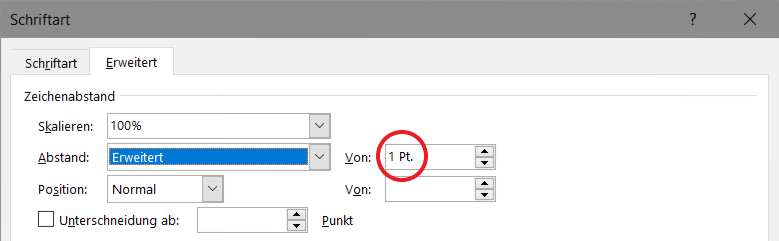
Schrift-Kombi für Projektarbeit im Bereich der Geschichtswissenschaften
Basiert nicht die ganze Diskussion darauf, dass es von Seiten der Hochschule die Vorgabe „12 pt“ gibt? Eben ohne zu Berücksichtigen, dass diese Angabe eigentlich völlig sinnlos ist. Und dann ist es eben doch irgendwie sinnvoll für diese Situation einfach mal diverse Schriften in 12 pt bezüglich der daraus resultierenden Seitenanzahl zu vergleichen. Der eine freut sich, dass er die geforderten zehn Seiten voll bekommt, der andere, dass er es schafft, so seinen Text auf zehn Seiten zusammenzustauchen.
Lesbarkeit, Mittellängen, Grauwert, ... alles unwichtig.
Wenn es so ist, verstehe ich es. Dann geht es nicht um Mittellängenvergleich, sondern um beliebige Verformungen zwecks Verschleierung des Umfangs. Nur wie sollte jemand den Schriftgrad auf einem Stück Papier oder in einem PDF überprüfen? Die Erfüllung dieser »sinnlosen« Vorgabe ist mit unterschiedlichen Schriften nicht nachprüfbar. Die Vereinheitlichung der abzugebenden Dokumente ist durchaus sinnvoll, um den Umfang vergleichen zu können. Früher war das die Normseite von 1800 Zeichen pro A4-Seite (30 Zeilen à 60 Anschläge).
Meine Herangehensweise wäre: Die Hochschule verlangt 12 Punkt und schreibt Arial oder Times New Roman vor. Das ist zwar einerseits unsinnig von Seiten der Hochschule, öffnet mir aber Freiräume. Nun möchte ich weder Arial noch Times New Roman verwenden, sondern ich suche mir eine  Alternative, die »irgendwie« nach Times aussieht. Und da ich nicht Martin Schröder bin, gibt es für mich hier auch nicht »die am besten geeignete Schrift«, sondern ich kann mir völlig schmerzfrei und ohne schlechtes typografisches Gewissen eine Schrift aussuchen, die mir bei gleicher optischer Größe (meinetwegen angelehnt an eine Times New Roman in 12 Punkt, damit es für den Professor »normal« aussieht) vom Platzbedarf her am besten behagt. Und selbst wenn das mit einer »Verschleierung des Umfangs« zu tun hat, dann doch eigentlich nur in einem Rahmen, den die Hochschule durch die Vorgabe Arial oder Times schon selbst, wenn auch unwissentlich, abgesteckt hat (und was die Vereinheitlichung zwecks Vergleichbarkeit ja ad absurdum führt).
Im übrigen dürfte es der Hochschule bzw. dem Professor, selbst wenn ihm der Unterschied zwischen Times und Arial erklärt würde, in den meisten Fällen trotzdem egal sein. Er will nur, dass die Arbeit für ihn gut les- und korrigierbar ist.
Das ist etwa so wie die Gewichts- oder Längenangaben bei den früheren Kleinstaaten, wo eine Elle überall unterschiedlich lang war.
Nun, eigentlich nicht, nur lässt sich die Schriftgröße kam an der x- bzw.  Versalhöhe messen, sondern diese Schriftgröße gibt an, auf welchem "Kegel" die Schrift sitzt, also der rechteckigen Fläche aus der alle Schriftzeichen - eben auch die diaktiischen Zeichen, die Ober und Unterlängen, Sonderzeichen usw ihren Platz finden müssen. Das war bei Bleilettern wunderschön sichtbar, bei digitalen Schriften ist das aber eher versteckt, und entspricht dem Zeilenabstand, wird kompress gesetzt.
Habe ich also eine Schrift mit deutlich großen Ober- und Unterlängen, muss ist zwangsläufig die x-Höhe deutlich kleiner machen, und die Schrift wirkt bei gleicher Schriftgröße auch kleiner.
Ich messe also tatsächlich immer mit der gleichen Elle, nur messe ich eben an einer relativ unsichtbaren Stelle.
Nun, eigentlich hast Du Recht. Man braucht also ein anderes Beispiel. Ich hatte ja an die PS-Zahl bei Kraftfahrzeugen gedacht, wo eine identische Leistung bei einem Motorrad doch etwas anderes bewirkt als bei einem Mittelklassewagen. Aber das trifft die Sache auch nicht so richtig.
also der rechteckigen Fläche aus der alle Schriftzeichen - eben auch die diaktiischen Zeichen, die Ober und Unterlängen, Sonderzeichen usw ihren Platz finden müssen.
Das nennt sich bei Fonts Bounding-Box und die Höhe der Bounding-Box wird zur Berechnung des Zeilenabstandes nicht herangezogen.
Schnecko wollte den Platzbedarf einiger Schriften ermitteln. Das geht eben nur, wenn man die wahrgenommene Größe berücksichtigt und über den Schriftgrad ausgleicht. Sonst vergleicht man Äpfel mit Birnen. Die wahrgenommene Größe ist bei der Trinité No1, No2 und No3 nahezu dieselbe, weil die Minuskeln der drei Versionen – von den Ober- und Unterlängen abgesehen – weitgehend dieselben sind. Die Version mit der größten Distanz zwischen Ober- und Unterlänge braucht aber einen Mindestzeilenabstand, damit keine Oberlänge mit einer Unterlänge in der darüber liegenden Zeile kollidiert. In dieser Hinsicht hat diese Version also den größten Platzbedarf. Bei einer Zeilenlänge von 16 cm, also der Länge, die Schnecko für seine Arbeit festgelegt hat, dürfte jener Mindestzeilenabstand aber irrelevant sein, weil der Zeilenabstand aus einem ganz anderen Grund groß sein muss, nämlich weil das Auge beim Sprung vom Ende einer Zeile die Folgezeile nicht fände.
Die drei Versionen der Trinité boten sich an, um zu beweisen, dass es keinen Sinn macht, für einen Vergleich des Platzbedarfs die Distanz zwischen Ober- und Unterlänge in verschiedenen Schriften anzugleichen. Eben weil die Form der Zeichen in diesem Fall nicht berücksichtigt werden muss.
Warum könnte der Vergleich des Platzbedarfs außer für Tricksereien von Studenten überhaupt sinnvoll sein? Wenn ein Format gegeben ist und ein bestimmter Duktus von Schrift, wird der Umfang in ähnlichen Schriften auch ähnlich sein. Kann ein Typograf es für erforderlich halten, eine Times mit einer Arial zu tauschen? Ich hatte neulich ein Buch zu entwerfen, für das eine Einsparung von Seiten gewünscht wurde im Vergleich zu einem ähnlichen Buch, das ich vorher gemacht hatte, um zu verhindern, daß es zu dick wird. Lösung: Änderung des Satzspiegels. Ich habe die Seite stärker gefüllt. Es sieht jetzt nicht mehr ganz so großzügig aus wie der vorhergehende Band, ist aber immer noch luxuriös und weit entfernt davon, knapp in den Rändern oder gar im Bund zu eng zu werden. Wir haben etliche Seiten eingespart, und die Ausartung in einen Wälzer konnte wunschgemäß verhindert werden. Das ist etwas ganz anderes als das Hantieren mit festen Maßen, wie es von Studenten für schriftliche Arbeiten verlangt wird. Auf die Idee, mir eine engere Schrift zu suchen, kam ich gar nicht. Denn würde diese für den gleichen Lektürekomfort nicht mehr Raum in der Höhe beanspruchen? Es wäre außerdem ein Aufwand, den ich nicht für nötig hielt, denn ich hätte mit den Schriften wieder etliche Zeit für Probeseiten und die diversen Einstellungen (Laufweite, Wortzwischenräume, Durchschuß) gebraucht. Um dann am Ende festzustellen, daß Schriftwechsel nichts bringt und ich doch an den Satzspiegel gehen muß?
Da Auszeichnungen immer eine graphostilistische Entscheidung sind, würde ich mich nach den Gepflogenheiten im Fachgebiet/Fachbereich erkundigen. Und wenn es sich um grundlegende Begriffe für deine Arbeit handelt (ich weiß das genaue Thema gar nicht …) gibt es in der Einführung der Arbeit sicher Gelegenheit, die Verwendung der Begriffe und Auszeichnungen zu beschreiben.